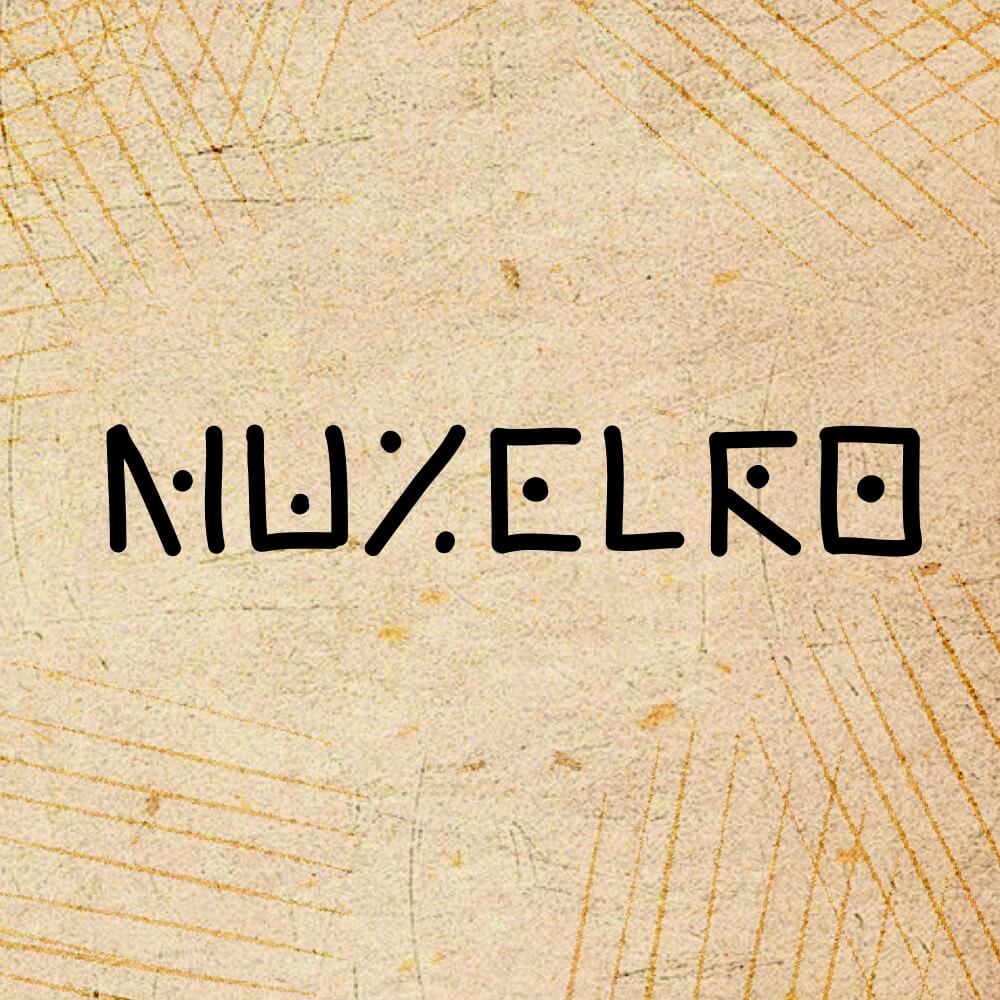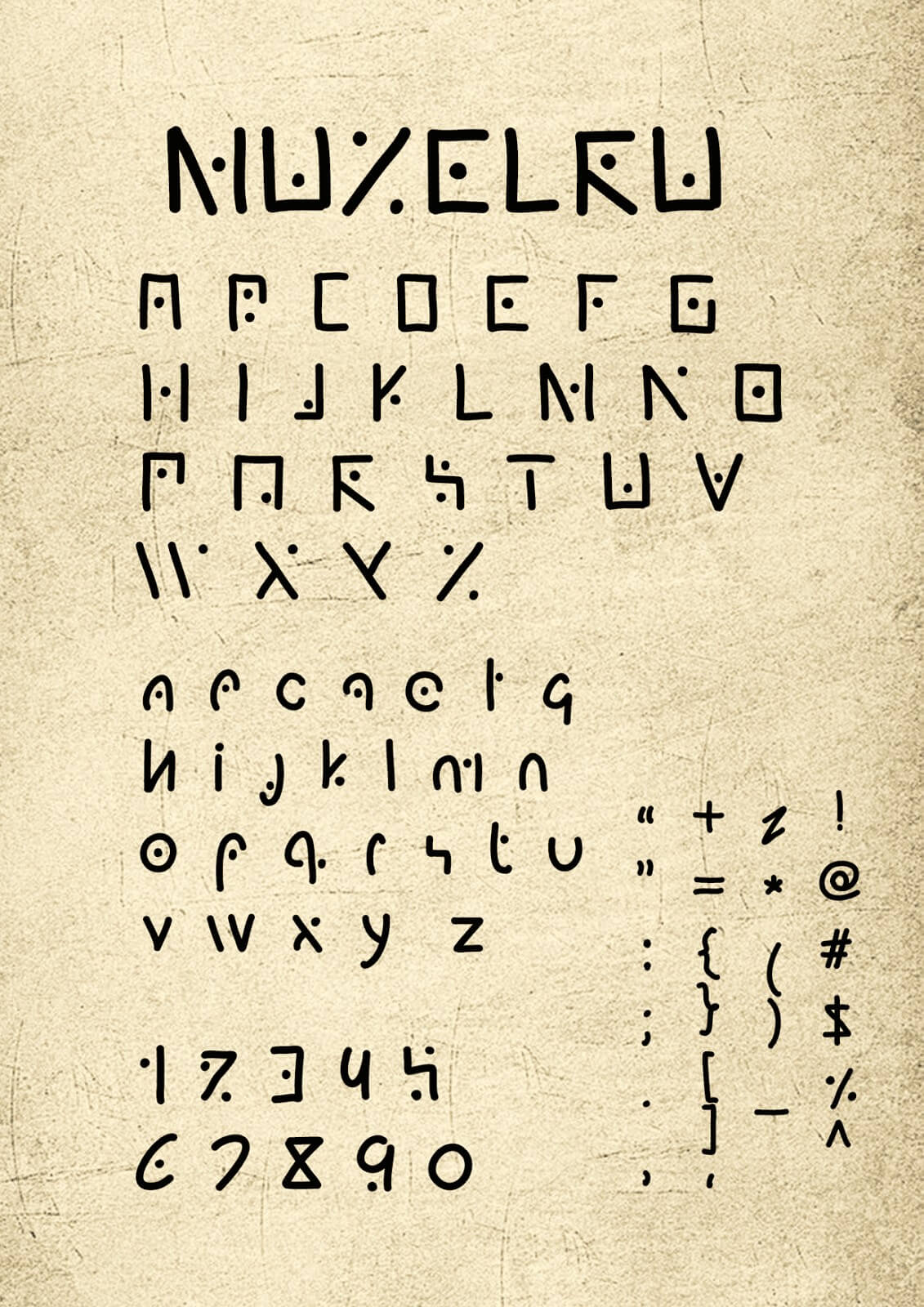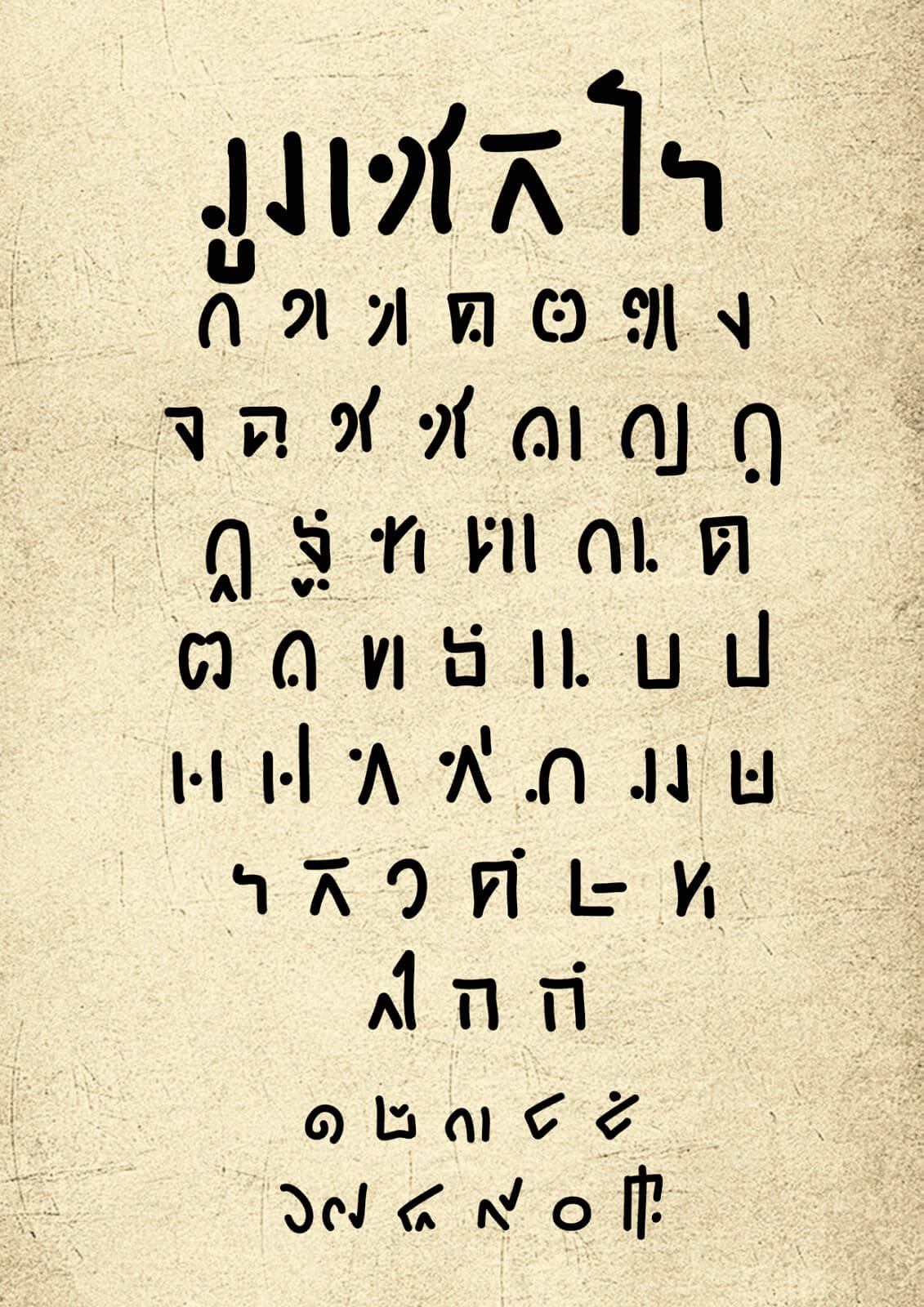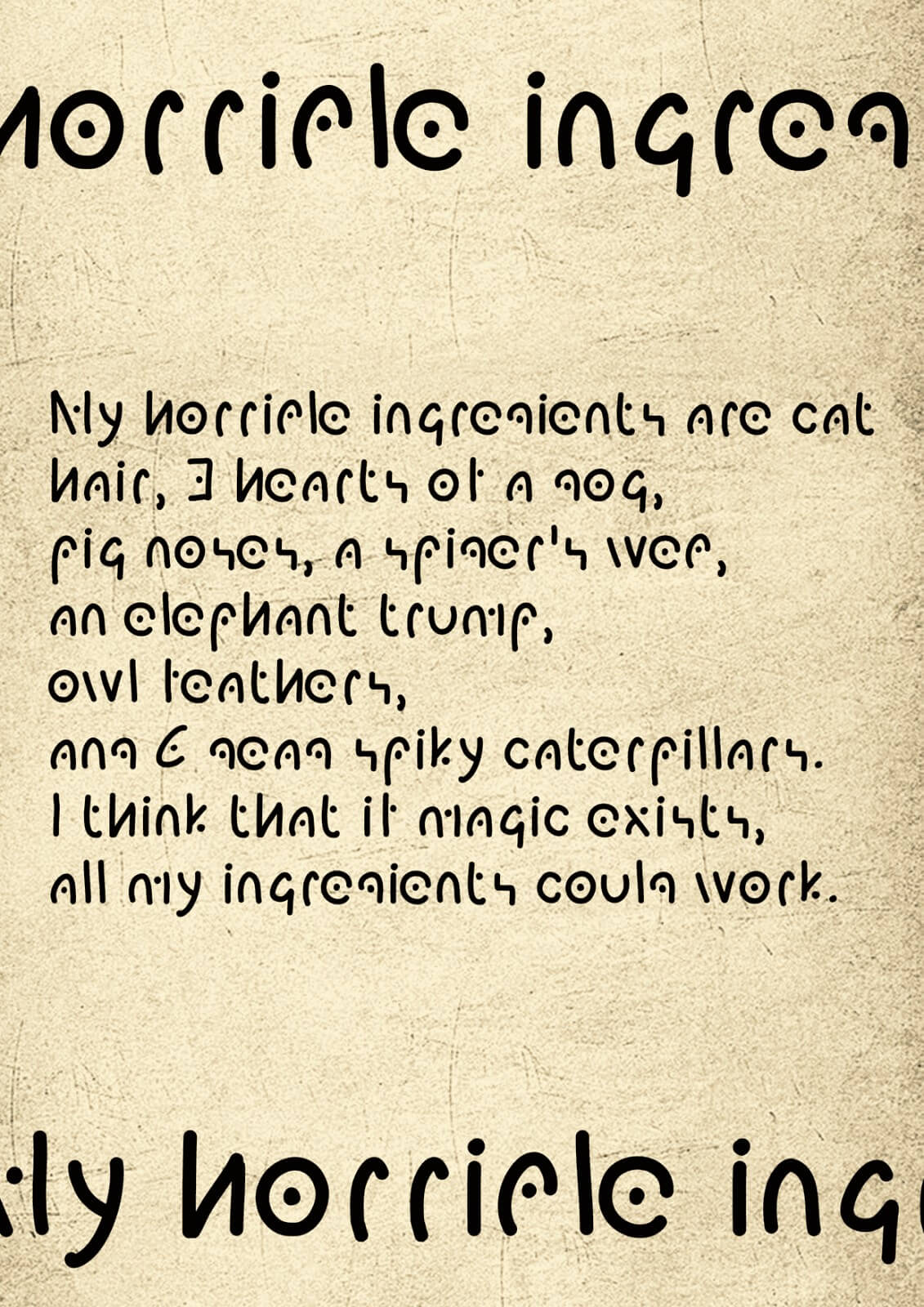
ฟอนต์ มูเซลโร muzelro – แรงบันดาลใจมาจากความขี้เกียจเขียนอักษรรูนในภาพวาด ตัวฟอนต์ออกแบบมาให้อ่านเหมือนจะได้แต่ไม่ ทำให้ตัวอักษรดูดีอย่างเดียว ไม่ต้องให้คนอ่านได้